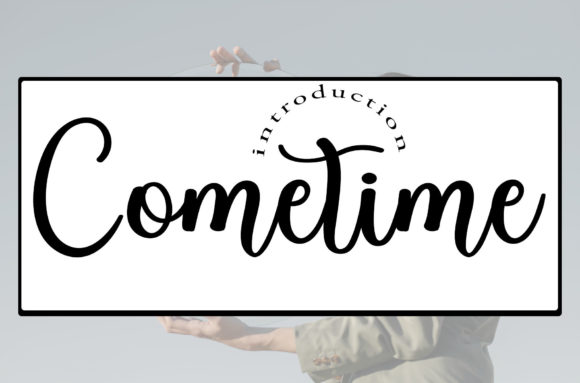
Cometime
Việc tìm kiếm các thành phần thiết kế phù hợp có thể là một thách thức, nhưng Cometime cung cấp một bộ sưu tập đặc biệt giúp nâng tầm công việc của bạn ngay lập tức.
Được chế tác với độ chính xác cao, Cometime cung cấp các vector sạch, kiểu chữ mượt mà và giấy phép thương mại để bạn yên tâm.